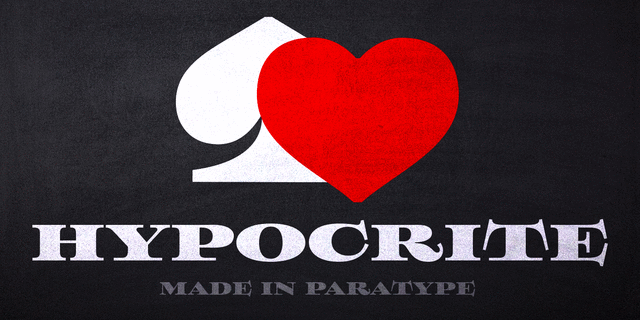
Шрифт разработан в Отделе наборных шрифтов НПО Полиграфмаш в 1986 на основе рисунков английских жирных шрифтов фирмы Леман (С.-Петербург) середины XIX века. Представляемая цифровая версия разработана в фирме ПараТайп (ПараГраф) в 1992 (дизайнер Владимир Ефимов). Предназначен для применения в рекламе и акциденции.
Ассоциации c семейством Standard PosterКачества и характер: